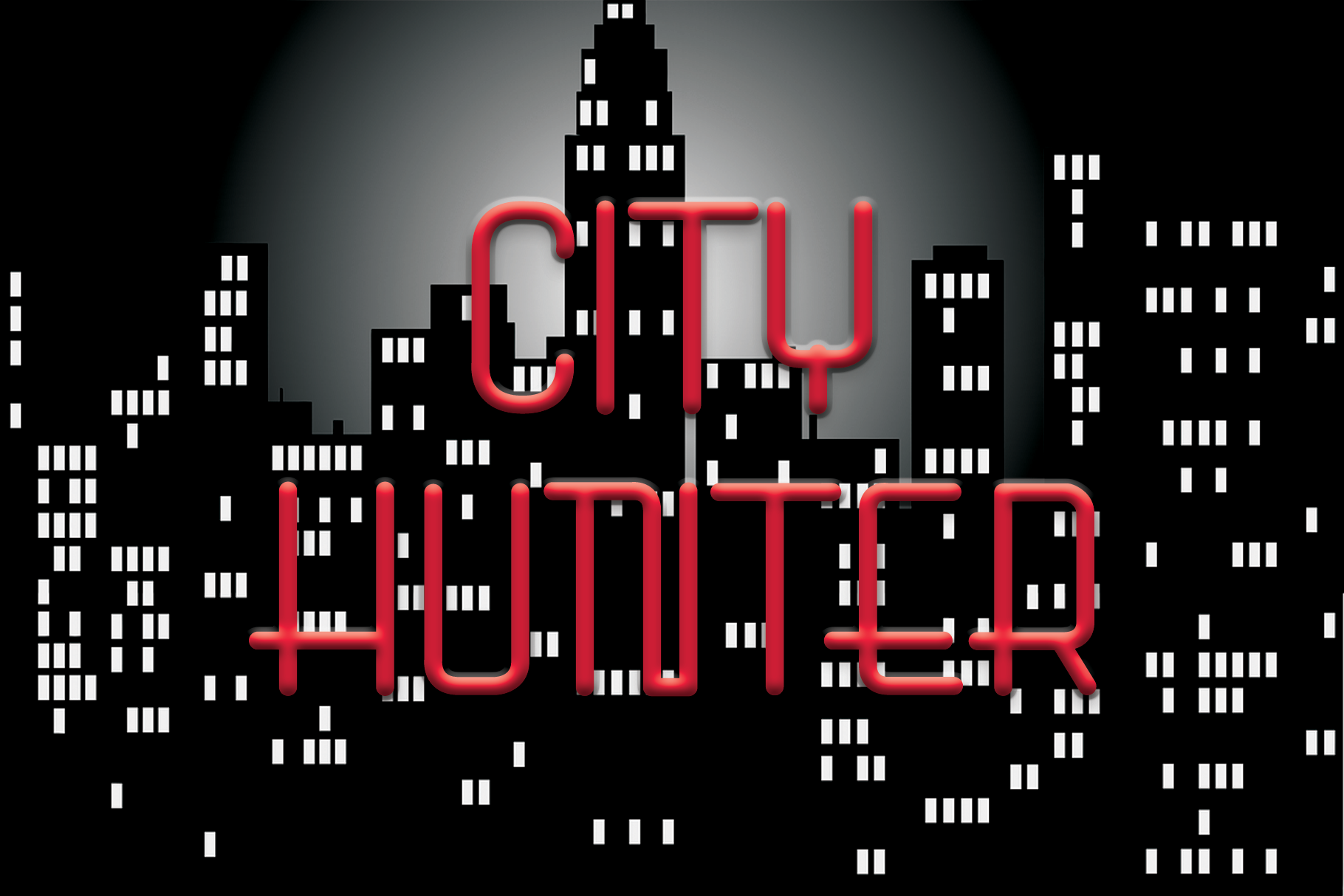
City Hunter Font – Download Grátis
A City Hunter Font é uma escolha perfeita para quem procura uma fonte moderna e minimalista que destaca-se dos demais. Ela foi projetada por el hotcig, um designer cuja visão se manifesta através de linhas simples e elegantes. Ideal tanto para o design web quanto para cartões de empresa ou qualquer outro uso que necessite de uma pegada única, essa fonte é perfeitamente adaptável a diversas finalidades. Se você está procurando por algo que dê seu projeto um toque distintivo sem perder a estética clara e direta característica do display fonts, City Hunter pode ser sua escolha. Suas linhas retas e curvas suaves proporcionam uma aparência contemporânea, perfeita para destacar mensagens essenciais em designs digitais ou impressos. Seja em uma página de site respeitosa ou em um cartão de visita elegante, City Hunter será o elemento diferenciador que adiciona uma personalidade única a seu projeto. El hotcig conseguiu criar algo verdadeiramente único com essa fonte moderna e minimalista, tornando-a uma opção muito procurada por designers de todo o mundo.